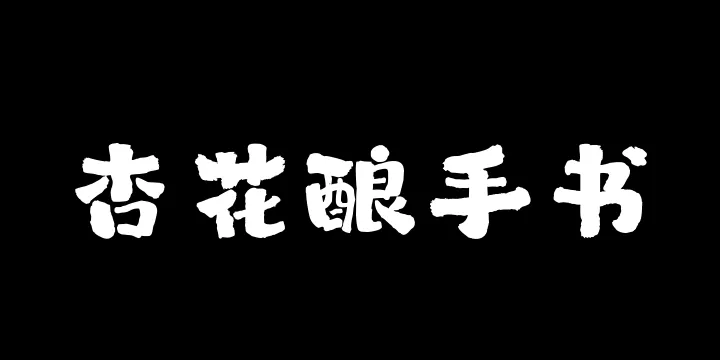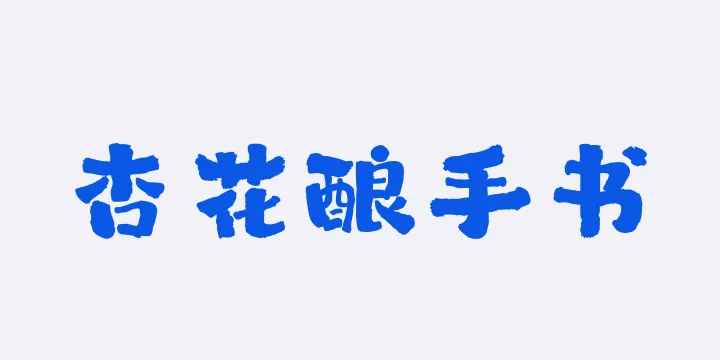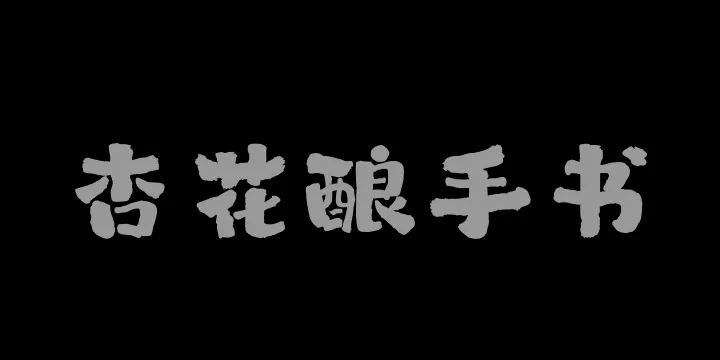
山海杏花酿手书W By 山海字库 商用字体
字体全名: 山海杏花酿手书W
字体简介: 山海杏花酿手书,是一款全新的卡通+古风毛笔字体,包含汉字9169个,符号200+个。该字体童趣可爱,结构多变灵动,字形活泼清新,造型生动有趣,具有灵活的适用性,天真俏皮又不失时尚感;同时兼具古风元素,古朴典雅,以毛笔风格的表现形式,使字体更别具一格,笔画的飞白效果使字体的气息更加流畅,笔画间的关系密不可分,同时也增加了字体的自由俏皮之感。